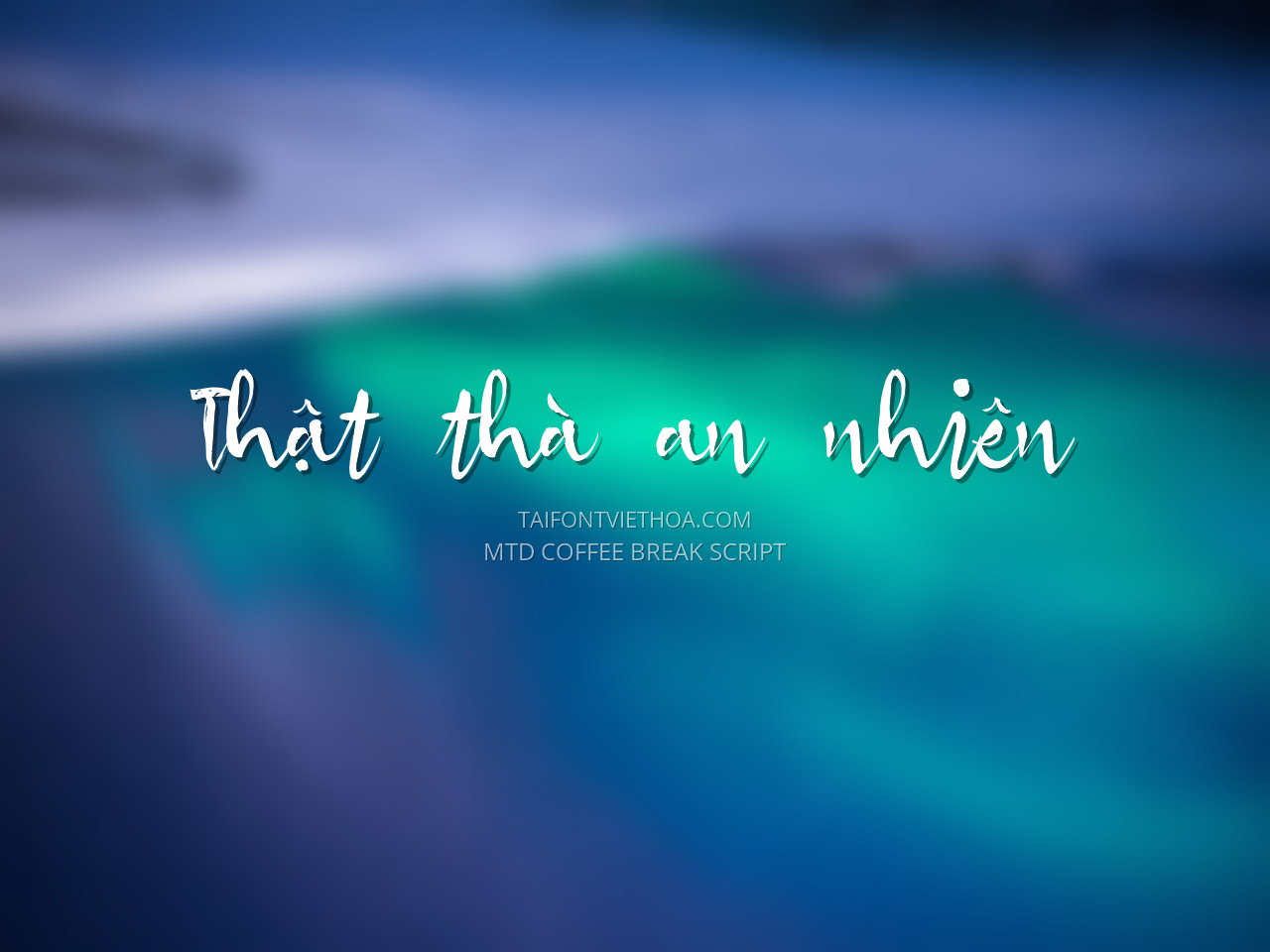
Font việt hóa MTD Coffee Break Script
Giới thiệu về font Coffee Break Script
Coffee Break Script là một font chữ viết tay (handwritten script) mang phong cách thân thiện, ấm áp và có chút ngẫu hứng như những dòng chữ được viết vội trong quán cà phê. Được phát triển bởi Motokiwo Type (MTD), font tái hiện nét viết tay mềm mại nhưng đầy tự nhiên, rất phù hợp với những thiết kế cần yếu tố cảm xúc và gần gũi. Phiên bản Việt hóa do chính MTD thực hiện, hỗ trợ đầy đủ tiếng Việt cùng hơn 70 ngôn ngữ khác, tạo điều kiện để ứng dụng rộng rãi trong cả môi trường thiết kế cá nhân lẫn thương mại.
Font này được taifontviethoa.com tuyển chọn và giới thiệu đến cộng đồng như một kiểu chữ lý tưởng dành cho những thiết kế mang tính cá nhân hóa, nhẹ nhàng và dễ tiếp cận. Với tinh thần phóng khoáng nhưng không kém phần tinh tế, Coffee Break Script giúp truyền tải cảm xúc một cách tự nhiên và hiệu quả trong từng dòng chữ.
Đặc điểm thiết kế và ứng dụng của font Coffee Break Script
Font Coffee Break Script được cấu trúc dựa trên các nét bút tay cong nhẹ, độ nghiêng vừa phải và có sự liên kết linh hoạt giữa các ký tự. Sự mềm mại trong đường nét cùng các chi tiết vẩy nhẹ giúp font trở nên sống động và tạo cảm giác “đời thường” nhưng vẫn đẹp mắt. Bộ font đi kèm các ký tự thay thế (alternates) và ligatures giúp tăng khả năng tuỳ biến trong thiết kế.
Ứng dụng lý tưởng: thiết kế menu quán cà phê, poster truyền cảm hứng, quote typography, thiệp mời, logo cá nhân, hoặc các sản phẩm thủ công và sáng tạo nghệ thuật. Ngành nghề phù hợp: ẩm thực, handmade, quà tặng cá nhân, thiết kế nội dung số, thương hiệu phong cách sống và các sản phẩm hướng tới sự gần gũi, tự nhiên và ấm áp.